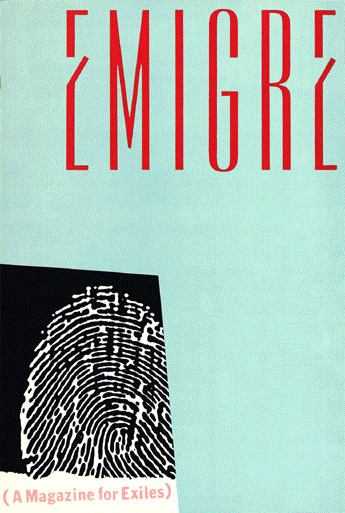
DaDa! Zuzana Licko et Rudy VanderLans? oui bien sûr!
Voici l’une des plus belles aventures typographiques des vingt cinq dernières années.
Fondé en 1984, Emigre, le magazine va publier 69 numéros qui vont nous surprendre tant par les nombreuses collections typographiques, décalées, transgressive et en même temps très ou trop expressives. Véritable source d’inspiration pour les directeurs artistiques, Emigre fait tout autant fonction commerciale que centre de recherche avancée sur les perceptions modernes du signe typographique.